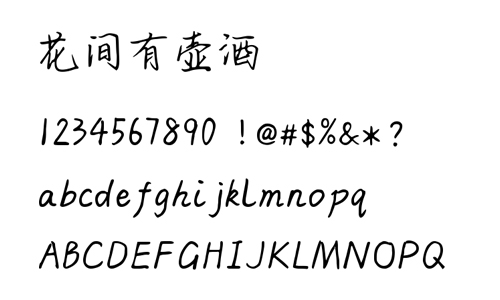
花間有壺酒是思雨字庫(kù)推出的一款硬筆手寫風(fēng)格字體,花間有酒,名曰相思;對(duì)影獨(dú)醉,其味自知。該字體風(fēng)格比一般的字體更有特色,連貫字跡顯得干練而不凌亂,清新簡(jiǎn)明,具有很好的視覺(jué)感。該字體是在國(guó)家標(biāo)準(zhǔn)簡(jiǎn)體字庫(kù)GB2312所包含6763漢字的基礎(chǔ)上,又增加了近200常用字,已經(jīng)覆蓋了大陸99.75%的漢字使用頻率,足以滿足日常需求。歡迎喜歡花間有壺酒字體的朋友前來(lái)下載使用。